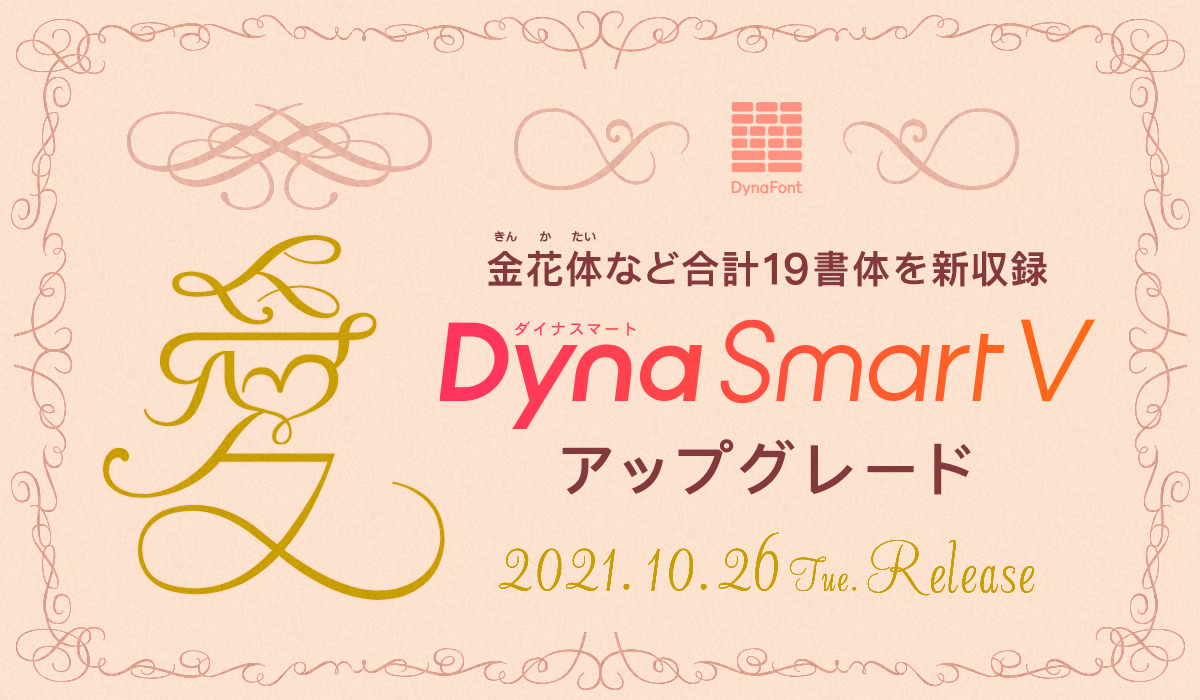
その他にも、上品で端正なスタイルで優美な楷書体「顔楷書W5/W7/W9」のOpenTypeフォントPro1-6N版およびPro1-6版や、国内外で数々のアワードを受賞している近年のダイナフォントを代表する新時代のゴシック体「金剛黒体 日本語」6ウェイトのTrueTypeフォント版も追加収録した。
ダイナフォント新書体「金花体」概要
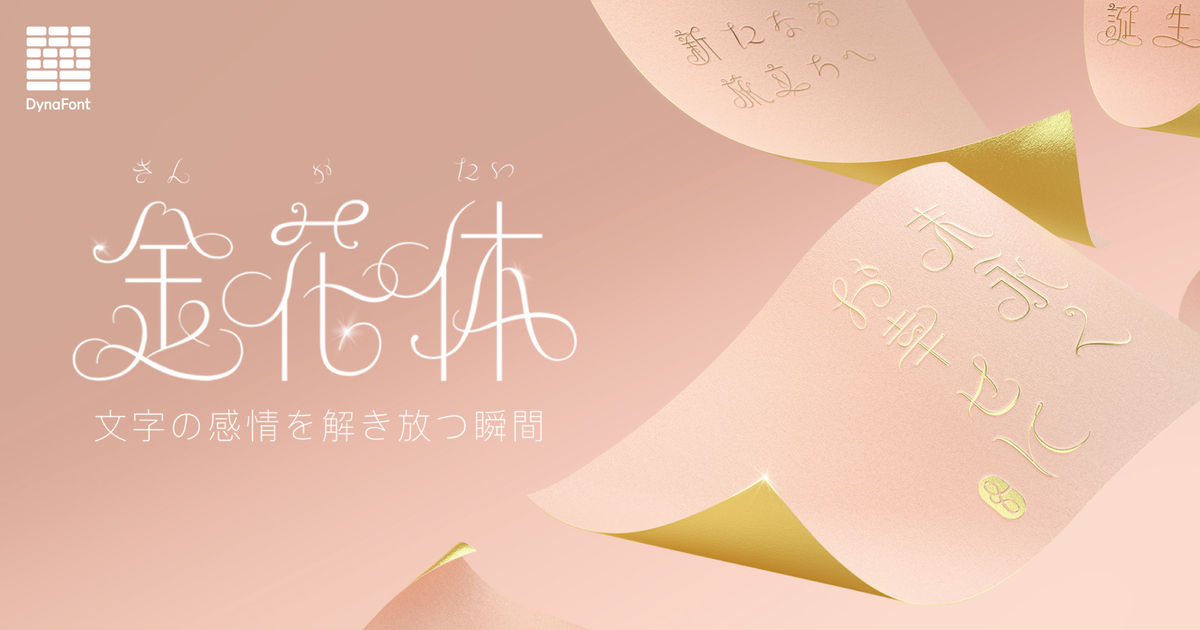
ダイナフォント新書体「金花体」
「金花体」は、金文の縦長の字形に中国戦国時代の青銅器「中山王方壺」の蟠龍の彫刻をカリグラフィーの流れるような曲線美で外側に伸ばすというこれまでのデザインの常識を取り払った書体。
「金花体」の特長である一筆書きのように文字を続けて書く手書き文字の筆記体は、これまで欧文特有のデザインだったが、漢字や仮名のデザインに取り入れるなど斬新な試みをしている。
また「金花体」は、カリグラフィーのエレメントから作成した装飾を文字セットから選んで自由に組み合わせることもできる。
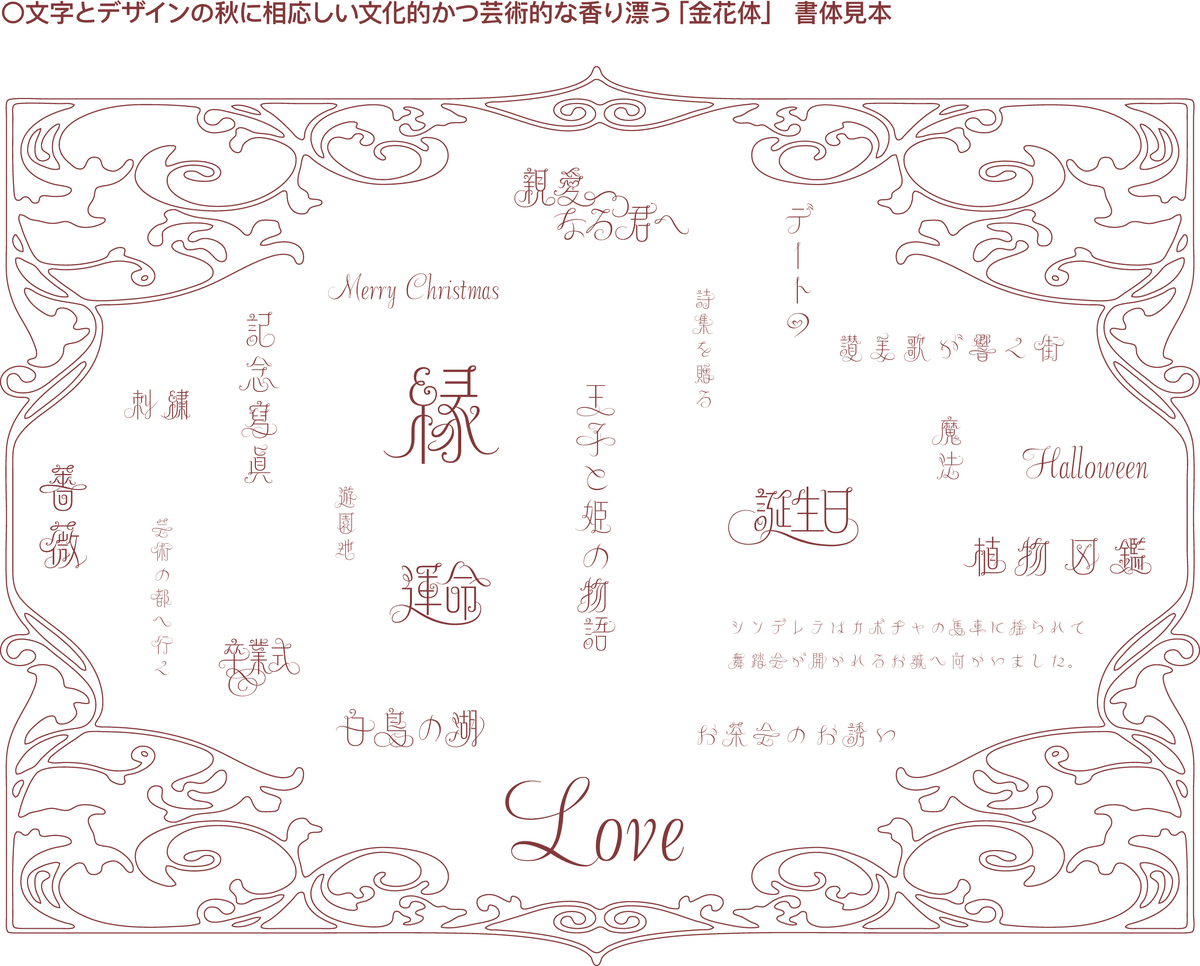
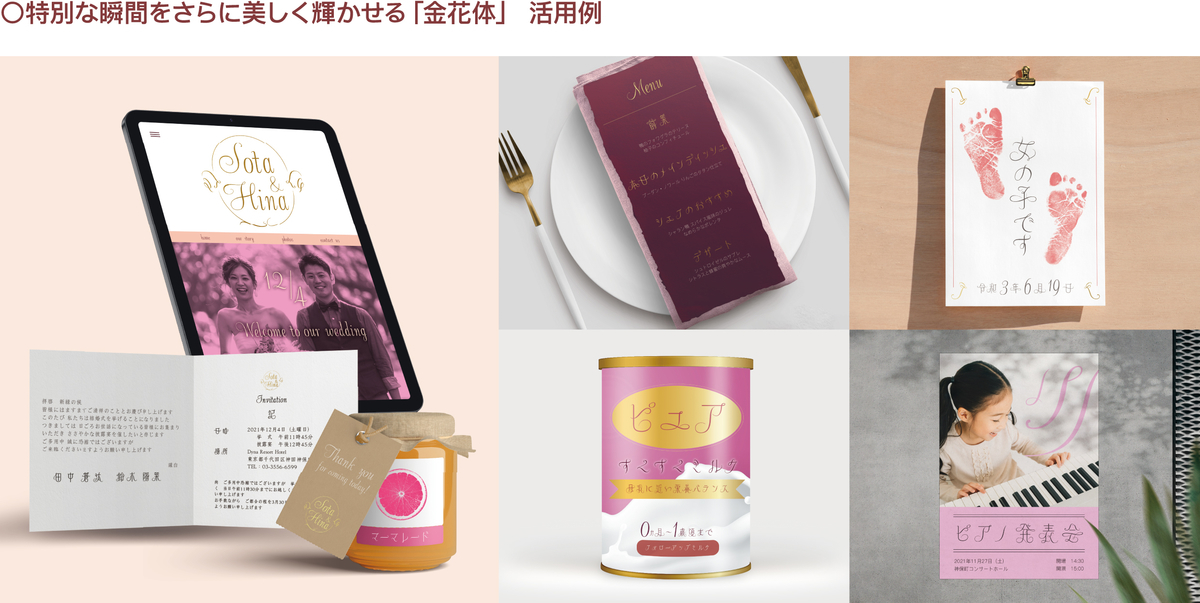
テロップ書体「太丸ゴシック体S」概要
テロップ書体「太丸ゴシック体S」は、DF太丸ゴシック体をベースに、液晶画面のあらゆるサイズでの表示に対応した書体として再設計することで、液晶画面表示においても柔らかな雰囲気による親しみやすさを鮮明に伝えることができる書体。
また、「太丸ゴシック体S」「極太丸ゴシック体S」「超極太丸ゴシック体S」の3種類のウェイトにより用途や場面に応じて柔軟に選択して最適な太さで使用できる。
「テロップ書体」は、液晶画面のあらゆるサイズに対応した書体で、さまざまなテロップで幅広く利用できる書体で、これまでに「平成明朝体S」4ウェイト、「平成ゴシック体S」4ウェイト、「UDゴシック体S」3ウェイト、「UD丸ゴシック体S」3ウェイト、「シネマ凜S」2ウェイト、「娥眉明朝体S」3ウェイト、「POPミックスS」3ウェイトを先行リリースしてきた。
「金剛黒体」概要
「金剛黒体」は、Ultralight、Thin、Light、Regular、Medium、Semiboldの6ウェイトで展開するゴシック体ファミリー。
シンプルで洗練されたストロークに加え、従来の書体より懐を広げたことで生まれたはっきりとした構造は、視認性を向上させ、また、文字全体に明るく澄みきったような空気感により、あらゆる文書において快適な読み心地をもたらす。
本文での使用から、見出しやキャプションなどに6ウェイトを柔軟に使い分けることで、洗練された文字による統一感のあるレイアウトを作成することができる。